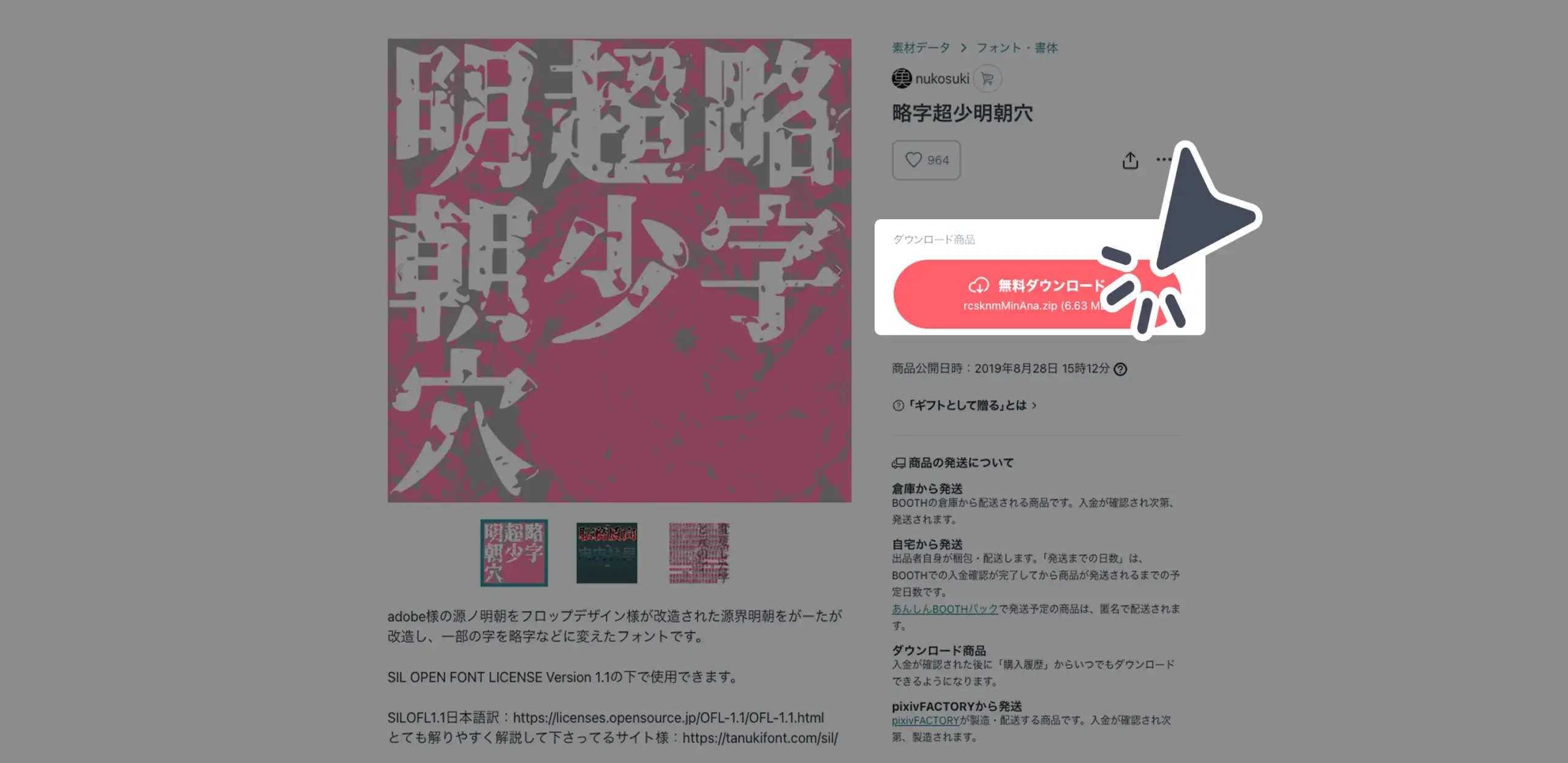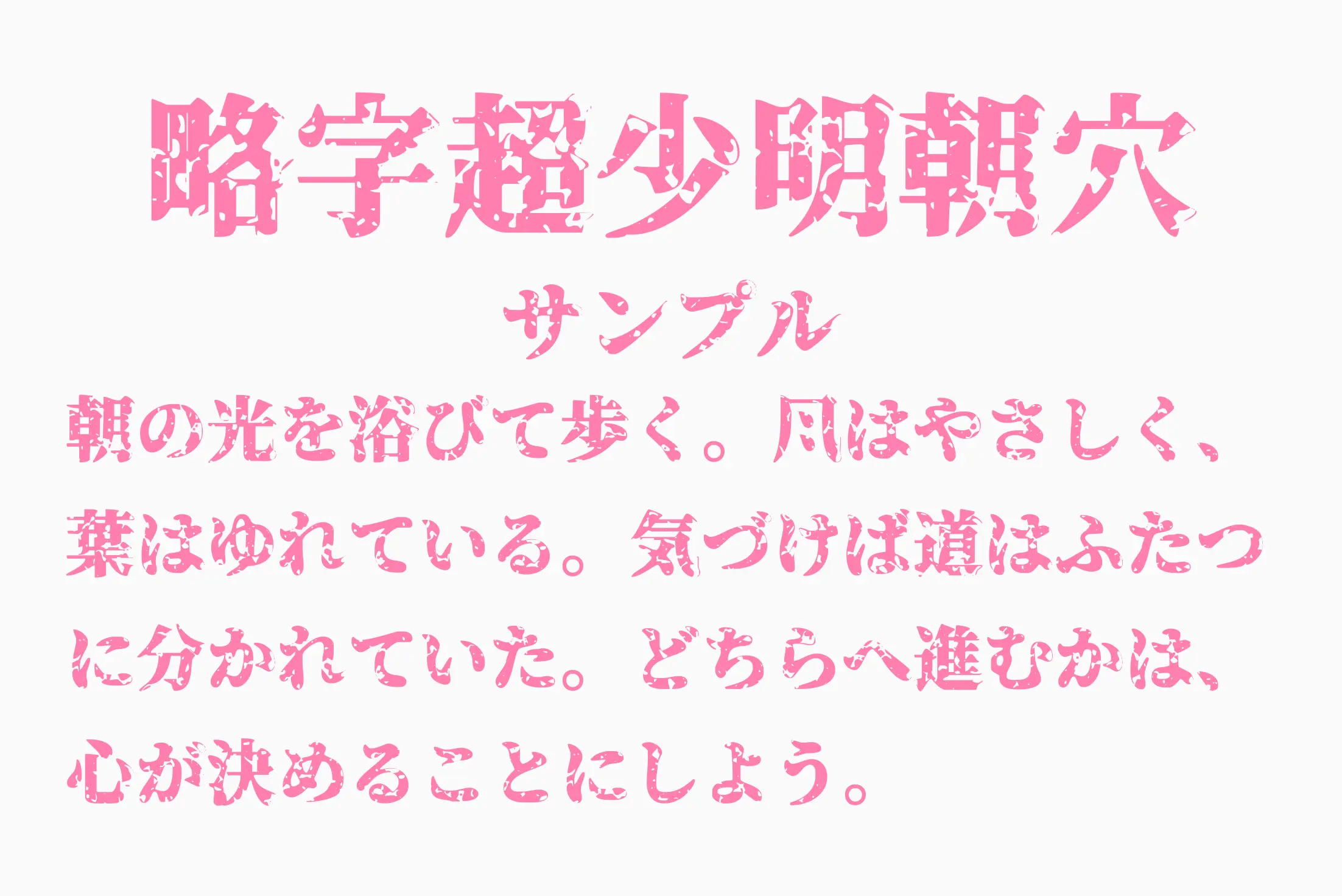
画数の多い漢字や珍字に対して視覚的な違和感や過剰表現を楽しむことができる実験的書体です。背景に見えるのは「少ない文字数で構成された作品群」や「書かれなかった文字たち」が浮かび上がるような美学。思想性やアート性を込めた作品、前衛的なビジュアル表現に最適です。
略字超少明朝穴
画数の多い漢字や珍字に対して視覚的な違和感や過剰表現を楽しむことができる実験的書体です。背景に見えるのは「少ない文字数で構成された作品群」や「書かれなかった文字たち」が浮かび上がるような美学。思想性やアート性を込めた作品、前衛的なビジュアル表現に最適です。